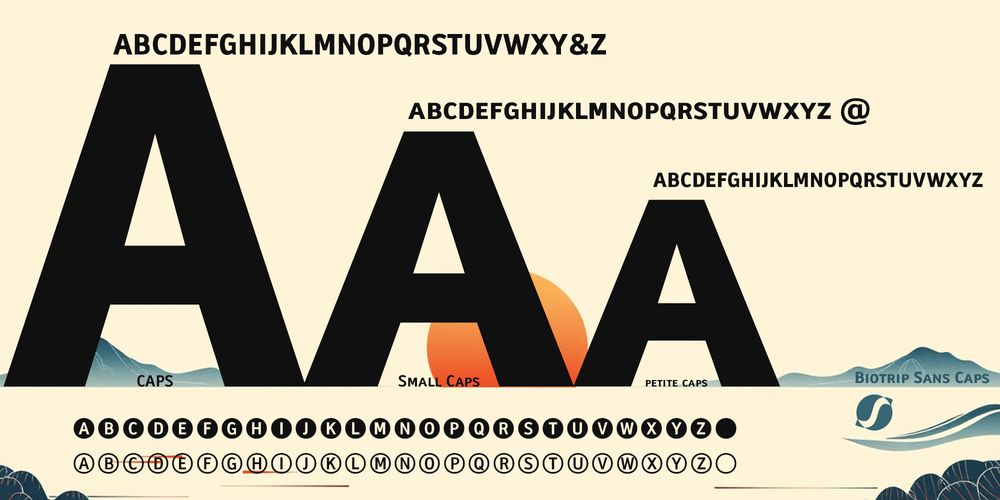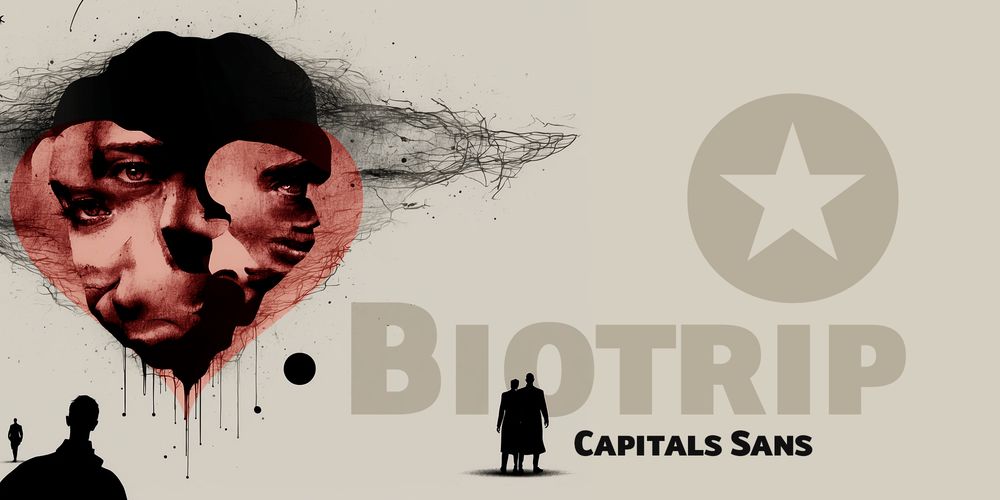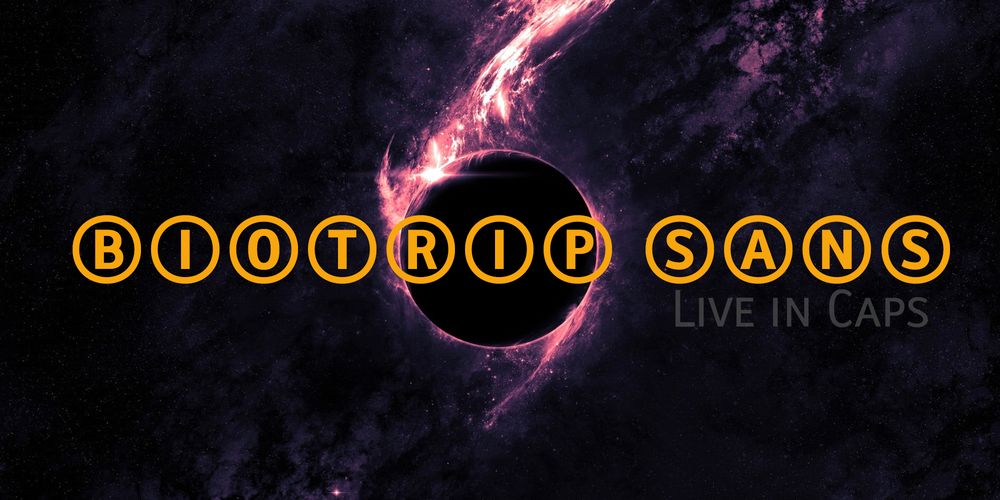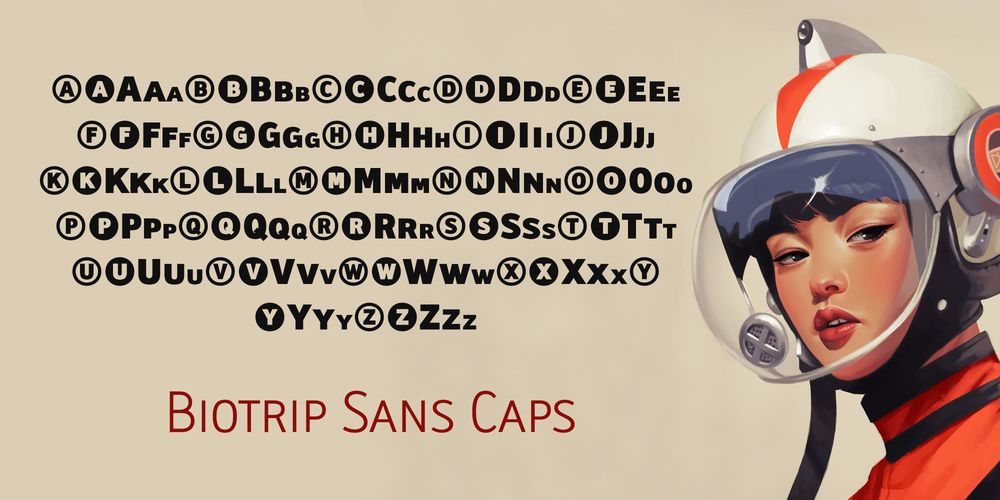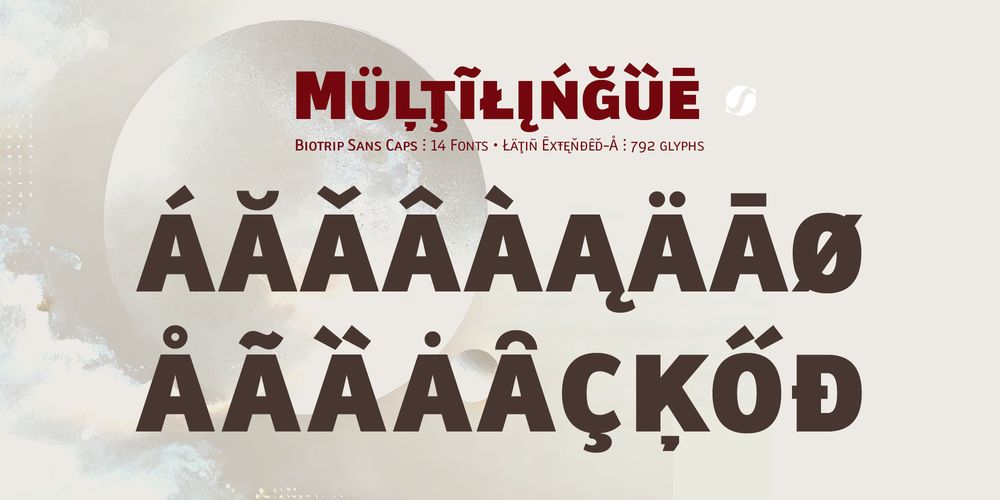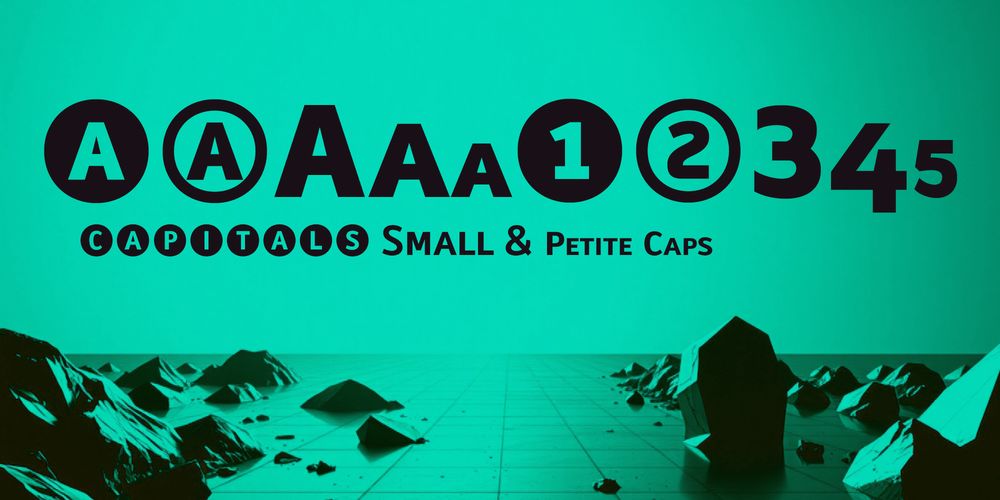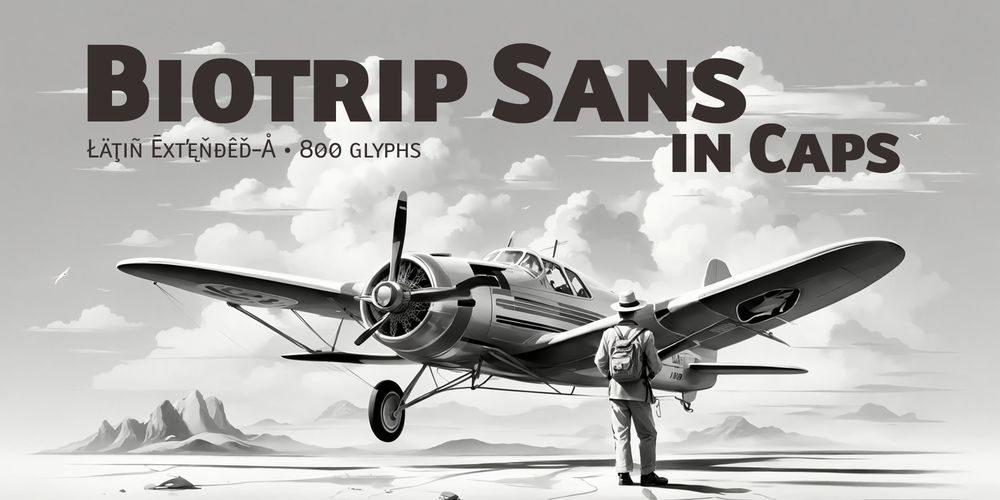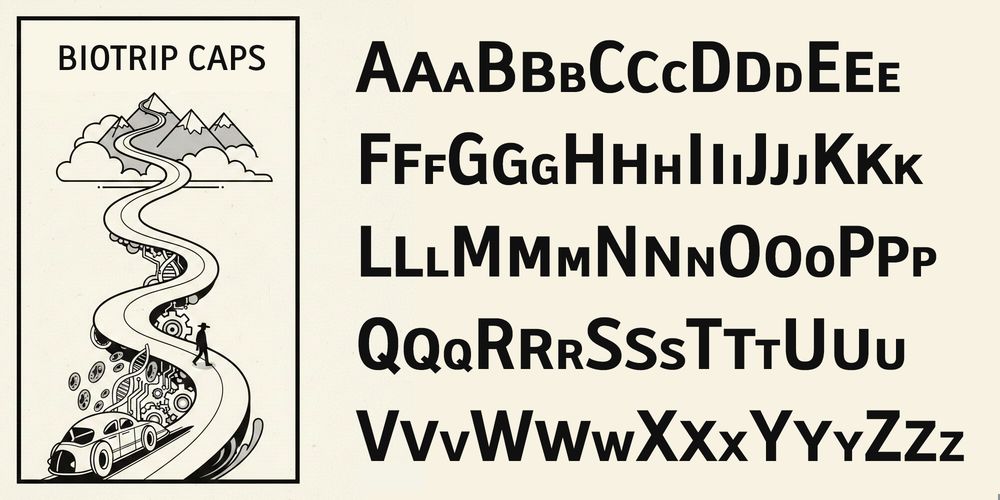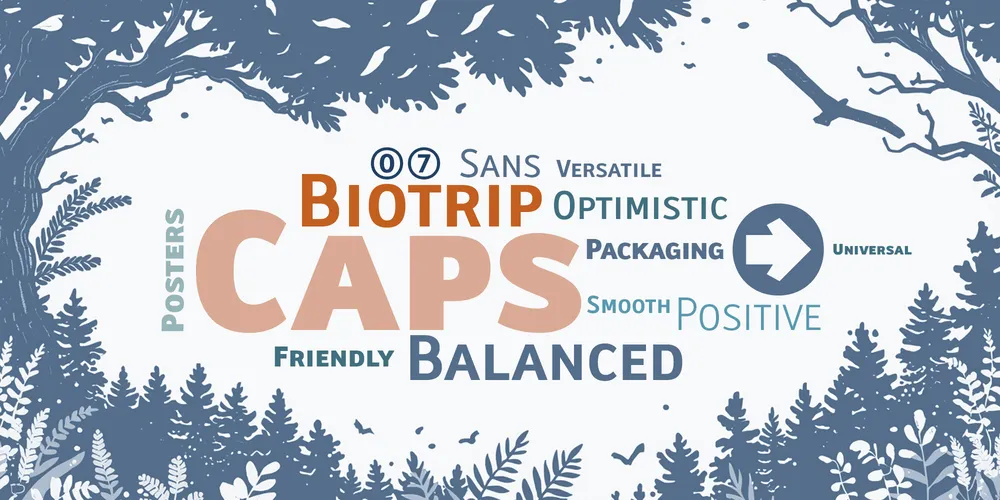
Estilo: Sans Serif, Display, Humanist, Capitals, Small Caps
Proporción: Light, Regular, Medium, Semi Bold, Bold, Extra Bold, Black
Glyphs: 800
Alternates: 181
Latin-Extended: Latín Básico, Europa Occidental, Central & Oriental.
Funciones OpenType: Additional languages, All Alternates, Bitcoin, Capital Spacing, Contextual Alternates, Denominators, Discretionary Ligatures, Fractions, Historical Forms, Inferiors, Kerning, Localized Forms, Numbers Small Caps, Numerators, Oldstyle Figures, Ordinals, Petite Caps, Scientific Inferiors, Slashed Zero, Small Capitals, Standard Ligatures, Stylistic Set, Subscript, Superior letters, Superiors, Superscript.
800 glyphs w/ 180 alternates: Numbers & Letters
Tipografía premium en mayúsculas para branding
Mayúsculas como lenguaje tipográfico
Las sans en mayúsculas —y los sistemas de small caps o petite caps— poseen algo profundamente tipográfico y, a la vez, casi filosófico: eliminan la jerarquía entre ascendentes y descendentes para construir un lenguaje más horizontal, más estable y más consciente del espacio que habita.
A diferencia de las mayúsculas regulares simplemente escaladas, las verdaderas small caps están diseñadas específicamente para mantener el color y el ritmo del texto. El resultado son jerarquías visuales sólidas que no interrumpen el flujo natural de lectura.
En Biotrip Sans Caps exploro la tensión entre control y gesto, entre forma racional y trazo humano. Es esa calidez la que rompe la frialdad del píxel y establece una conexión real, casi táctil, con quien la lee. Su construcción es orgánica y viva, con curvas que fluyen. Las formas son abiertas y amables, pensadas para ofrecer una excelente legibilidad en cuerpos pequeños, pero también para sostener grandes titulares con carácter, equilibrio y presencia.
Tipografía multipropósito
Biotrip Sans Caps es una tipografía multipropósito, refinada hasta el último detalle. Incluye siete pesos —Light, Regular, Medium, Semi Bold, Bold, Extra Bold y Black— que permiten construir sistemas visuales sólidos, modulables y expresivos.
Cada variante ha sido cuidadosamente diseñada para preservar la esencia humanista de Biotrip Sans, con la autoridad de las formas mayúsculas.
- 08 juegos completos de números, pensados para contextos editoriales, técnicos y experimentales.
- 03 juegos de mayúsculas y 04 juegos de minúsculas en petite caps, que permiten crear jerarquías visuales ricas y flexibles.
- Funciones OpenType avanzadas, con una creación impecable de fórmulas: inferiores, superiores, ordinales y más.
- Signos de puntuación decorativos, desde Tricolon, referencemark, dottedcross y asterism hasta therefore y because, cada uno como un pequeño universo expresivo.
- Anotaciones y símbolos, con dos estilos de Alternate Annotation Forms y flechas direccionales en círculos blancos y negros.
- Ligaduras estándar, discrecionales y contextuales, junto con soporte monetario global que incluye las principales criptomonedas.
- Soporte Latin Extended-A, preparado para una comunicación amplia y diversa, sin fronteras lingüísticas.
Biotrip Sans Caps no es solo una variante en mayúsculas: es una reflexión tipográfica sobre la forma, el ritmo y la presencia.
Está pensada para diseño editorial, donde se requieren jerarquías claras sin renunciar a la calidez, cartelería, identidad visual, logotipos, packaging y señalización. Es ideal para proyectos que necesitan claridad, pero también intención. Su legibilidad es excepcional, incluso en usos prolongados o sistemas complejos:
Para la marca que quiere erigirse como un logotipo memorable, el póster que debe detener la mirada con elegancia, el libro que guía la lectura con suavidad, el embalaje que habla al tacto antes de ser abierto, la señalización que ordena el espacio con amabilidad o para la imagen corporativa que construye confianza.
Sistema tipográfico Biotrip
Nunca pensé Biotrip como una sola tipografía. Desde el inicio la imaginé como un sistema: un lenguaje coherente capaz de adaptarse a distintas voces sin perder identidad. Por ahora Biotrip Sans, Biotrip Sans Caps y Biotrip Serif, ellas no compiten entre sí; dialogan. Cada una ocupa un lugar preciso dentro de una misma gramática visual.
Biotrip Sans: La voz base. Fluida, cercana y humana. Funciona como texto principal y cuerpo narrativo, donde la lectura se vuelve natural y continua. Su carácter humanista y construcción orgánica la hacen ideal para textos largos, interfaces y proyectos editoriales.
Biotrip Sans Caps: Estructura y presencia. Al trabajar con mayúsculas y petite caps, elimina el ruido vertical y genera una línea tipográfica estable, horizontal y consciente del espacio.
Biotrip Serif: Peso, memoria y profundidad. Sus serifas slab de inspiración egipcia, combinadas con detalles lapidarios, aportan anclaje visual y carácter editorial. Conecta el sistema con la tradición tipográfica sin renunciar a una estética contemporánea. Destaca en titulares, citas, marcas y proyectos donde la identidad necesita solidez y expresión.
El equilibrio del sistema Biotrip se construye sobre una base común: proporciones compartidas, modulación orgánica, ritmo interno y una coherencia formal que permite combinar las familias sin fricción.
Tres familias, un mismo ADN. Cada una aporta una energía distinta: fluidez, afirmación y raíz.